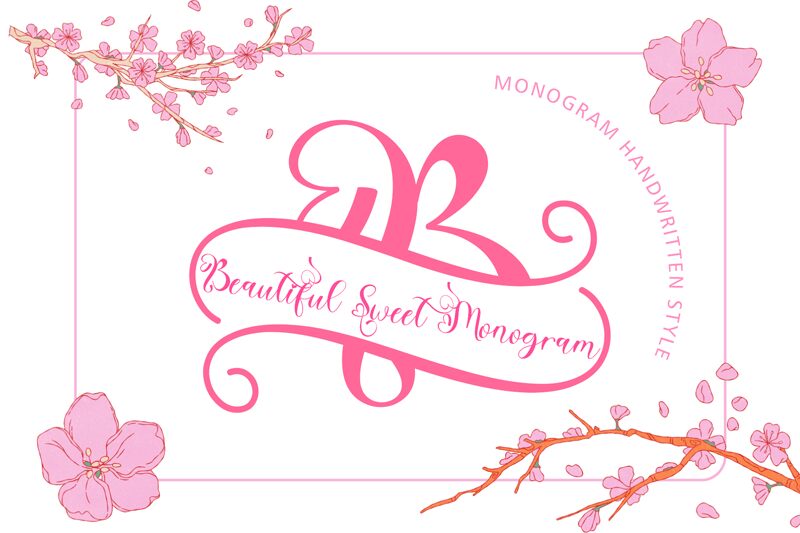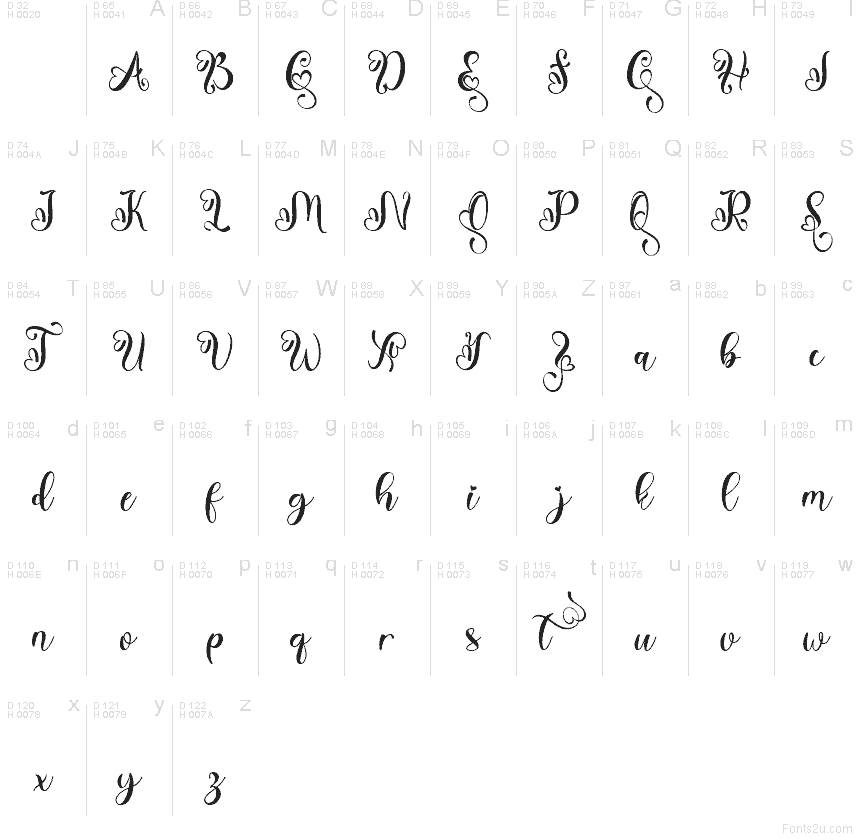
Beautiful Sweet Regular
Beautiful Sweet od Yoga Letter je bezplatné skriptové písmo pro svátek svatého Valentýna, které vyniká svými smyčkami a měkkými, romantickými tahy. Písmena se propojují v plynulém rukopisném stylu, přičemž dekorativní velké písmeno, které se stáčí do podoby srdce, a dlouhé, rozmáchlé zakončení dodávají této rodině písma její osobitý charakter.
Beautiful Sweet je bezplatný font, který skvěle funguje na svatebních oznámeních, valentýnských přáních, milostných dopisech, logách i na balení luxusního zboží, protože jeho plynulý rukopis dodává osobní, autentický dojem. Hodí se také pro grafiku s citáty, etikety produktů a dekorativní příspěvky na sociální sítě, kdy chcete, aby samotné písmo vytvořilo atmosféru bez potřeby dalších ozdob.